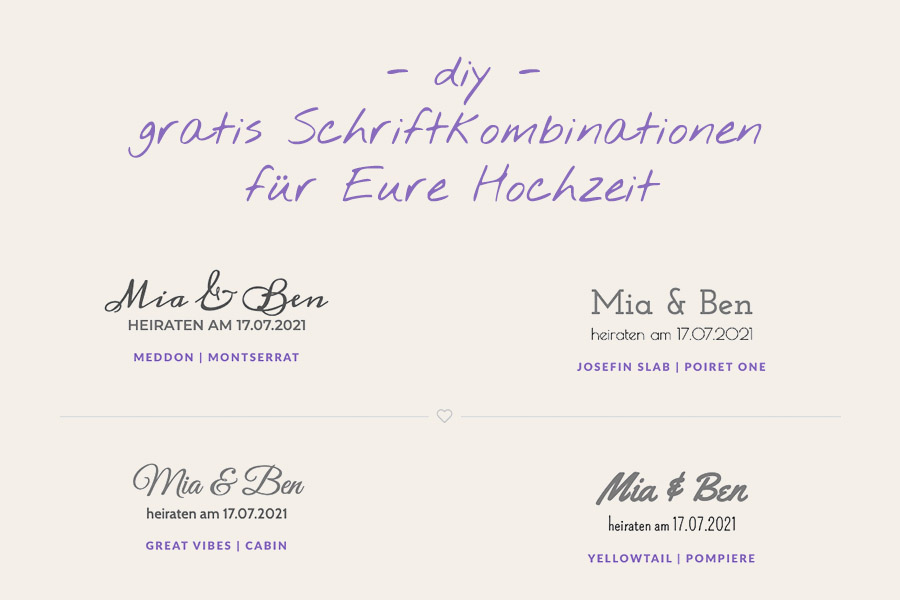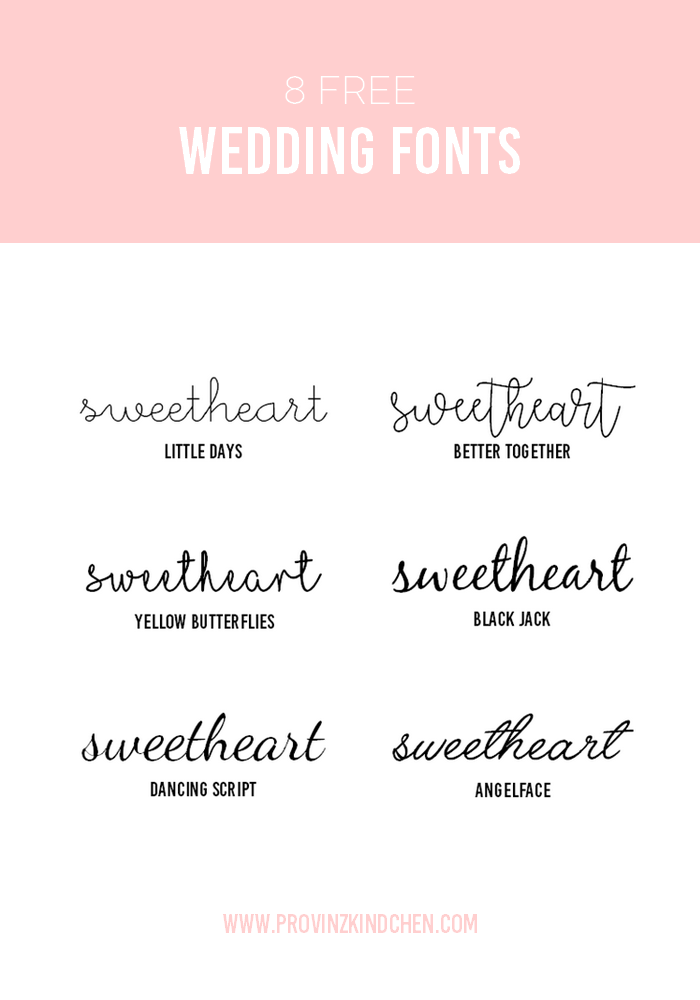
Schriftart Fur Hochzeit
Ich bin gerade dabei Einladungskarten zu gestalten, welche elegant daherkommen sollen und für den RückseitenText hoffe ich auf Eure Mithilfe bei der Schriftwahl Aus einem ganzen Zoo von Möglichkeiten die ich vorgelegt habe hat sich recht schnell herauskristallisiert daß es eine Serifenschrift s.
Schriftart fur hochzeit. Schriftart für ,,Hochzeit" Dieses Thema im Forum "Grafikdesign und Fotografie" wurde erstellt von InFected, 15 August 07. CocktailRezepte für die Hochzeit Die Drinks von Cassie Winslow sind die perfekte Besetzung für Ihr Fest Auf ihrem InstagramAccount @decotartelette stellt Cassie Winslow nicht nur leckere. Hast du bis hierhin gescrollt, um die Fakten über hochzeit schriftart zu erfahren?.
Die richtige Schriftart für Eure Hochzeit zu finden, ist leider nicht ganz einfach Ein erster Anhaltspunkt ist, dass sie in allen Fällen gut lesbar sein sollte Immerhin wollt Ihr ja nicht, dass wichtige Infos übersehen werden. Dir richtige Schriftart für Einladungen, Danksagungskarten oder Menükarten zu finden, ist gar nicht so einfachDoch es gibt ein paar tolle Tools und Webseiten, die Dir dabei helfen, schnell den passenden Font zu finden!. Hochzeit Farbthemen Boho Hochzeit Deko Braut Dekor Hochzeit Rustikal Zeremonie Bogen Hochzeit Ideen Für Die Hochzeit How to Get Rid of Saggy Skin Health Care If you have ever asked yourself if there is a way to get rid of saggy skin, then you are not alone.
Nun, du hast Glück, denn hier sind sie Es stehen 407 superhelden schriftart auf Etsy zum Verkauf, und sie kosten im Durchschnitt 4,13 € Das gängigste Material für superhelden schriftart ist baumwolle Die beliebteste Farbe?. Hast du bis hierhin gescrollt, um die Fakten über hochzeit schriftart zu erfahren?. Egal für welche Hochzeitseinladung und Schriftarten ihr euch entscheidet, ihr werdet bestimmt eine passenden für euch als Paar finden In Canva findet ihr noch zahlreiche weitere EinladungsVorlagen und auch Schriftarten, falls oben keine passende dabei war.
Details Cursive Schriftart Hochzeit Schriftart Monogramm Cursive Schriftart für Cricut Font Svg Kalligraphie Schriftart Handschriftliche Schrift Cursive Schrift art Svg Dateien für Cricut Perfekte Dekoration für Hemden, Hüte, Einkaufstaschen, Kartenherstellung, Tassen, Wandkunst,. Es gibt jedoch durchaus ein paar Tricks, die dabei helfen, die richtige Schriftart für die Hochzeit zu finden und zu nutzen Wo gibt es schöne Schriften für die Hochzeit?. Testen Sie die installierten Schriftarten (bei Betriebssystemen Microsoft Windows 98, ME, NT, XP, 00, Vista und 7) für die Gestaltung von Einladungskarten, mit dem EinladungskartenDesigner bei einladungsformde Schöne kostenlose Schriftarten für Einladungskarten downloaden.